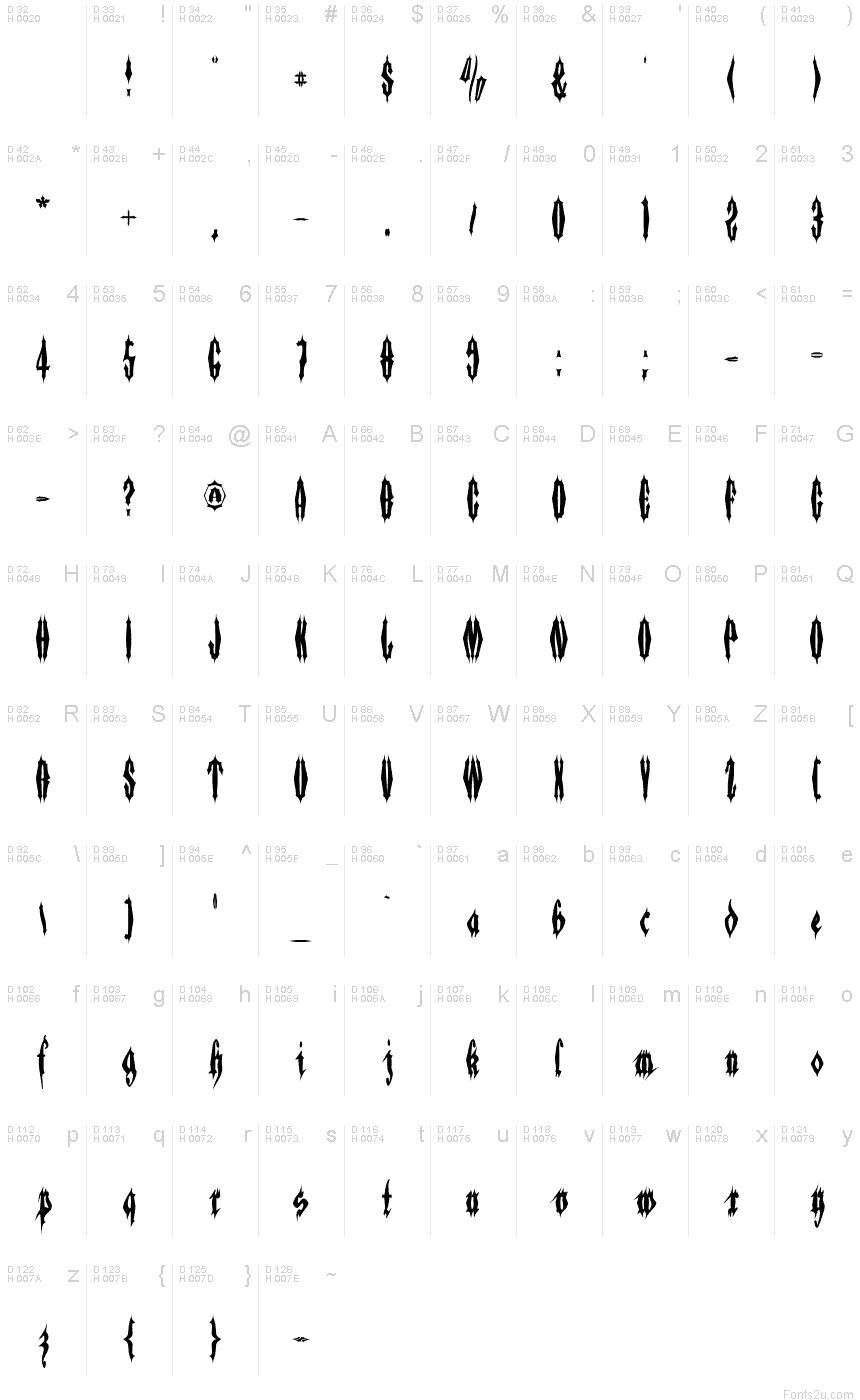
Applesauce 05, zaprojektowany przez Perry'ego Masona, to darmowy krój typu display o horrorowym charakterze, zbudowany z ostrych, zniekształconych kształtów liter. Długie kolce, haczykowate pociągnięcia i wyglądające na poszarpane krawędzie nadają napisom agresywną sylwetkę, z nieregularnymi kształtami przypominającymi wycięte ręcznie cienie.
Świetnie nadaje się do plakatów horrorów, ekranów tytułowych gier oraz grafik na imprezy halloweenowe, które wymagają surowej, złowrogiej tekstury. Ekstremalne punkty mogą również sprawdzić się na gadżetach zespołów metalowych lub okładkach albumów, choć litery potrzebują czystego tła i dużych odstępów, aby ich wąskie cięcia i spiczaste przedłużenia pozostały wyraźne.